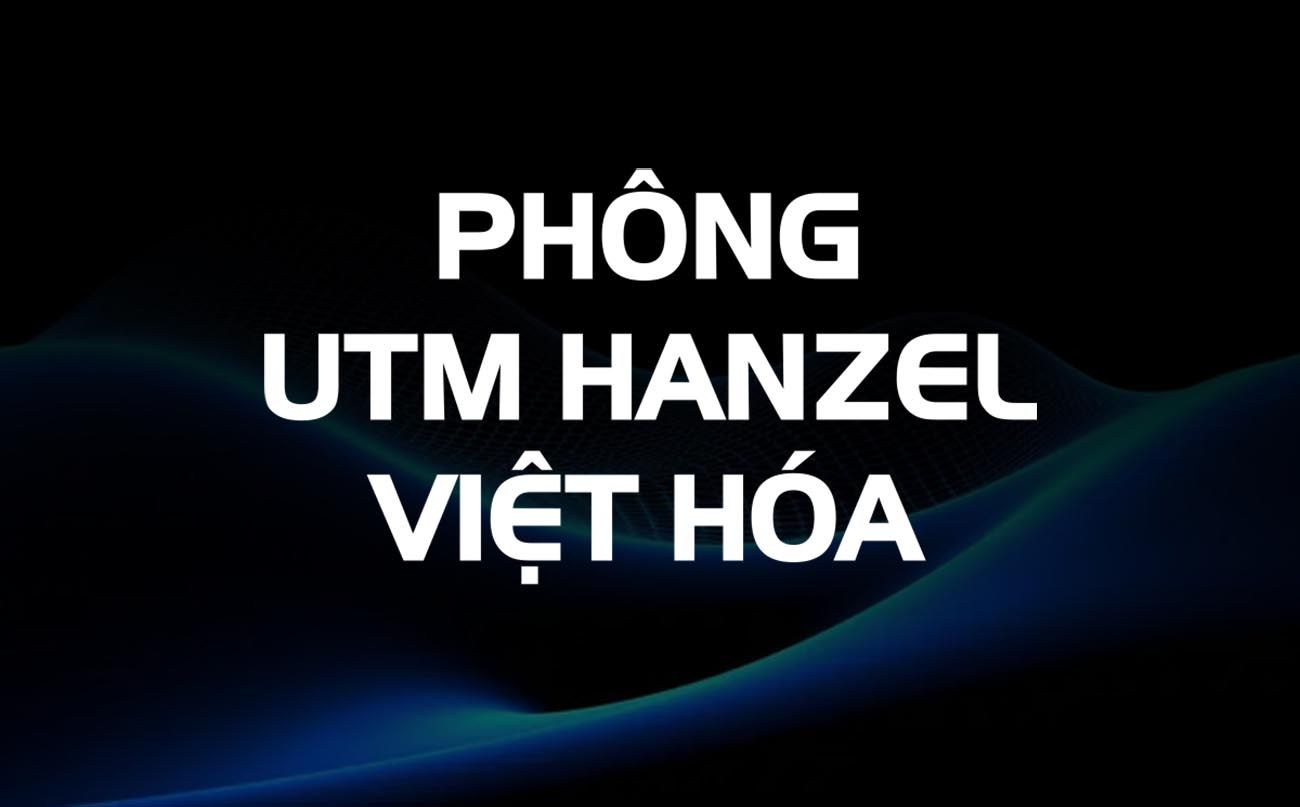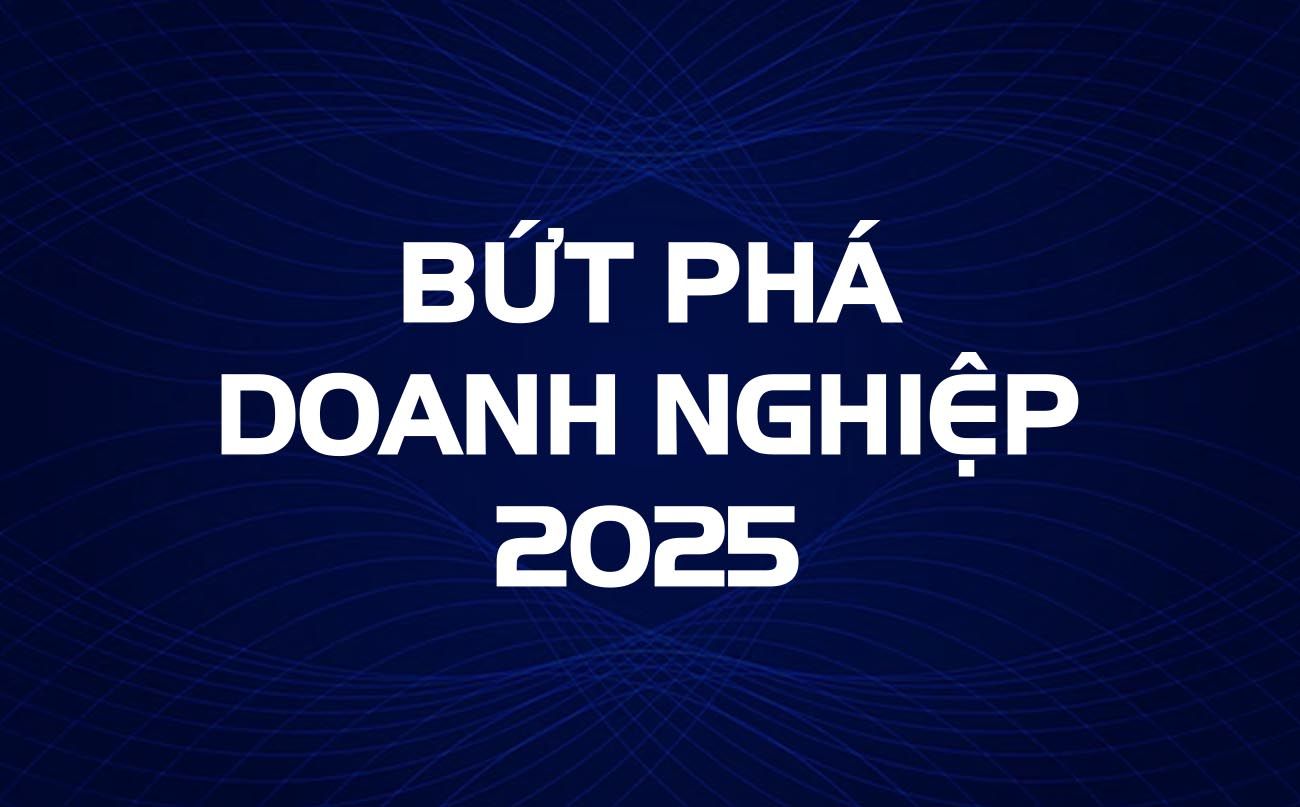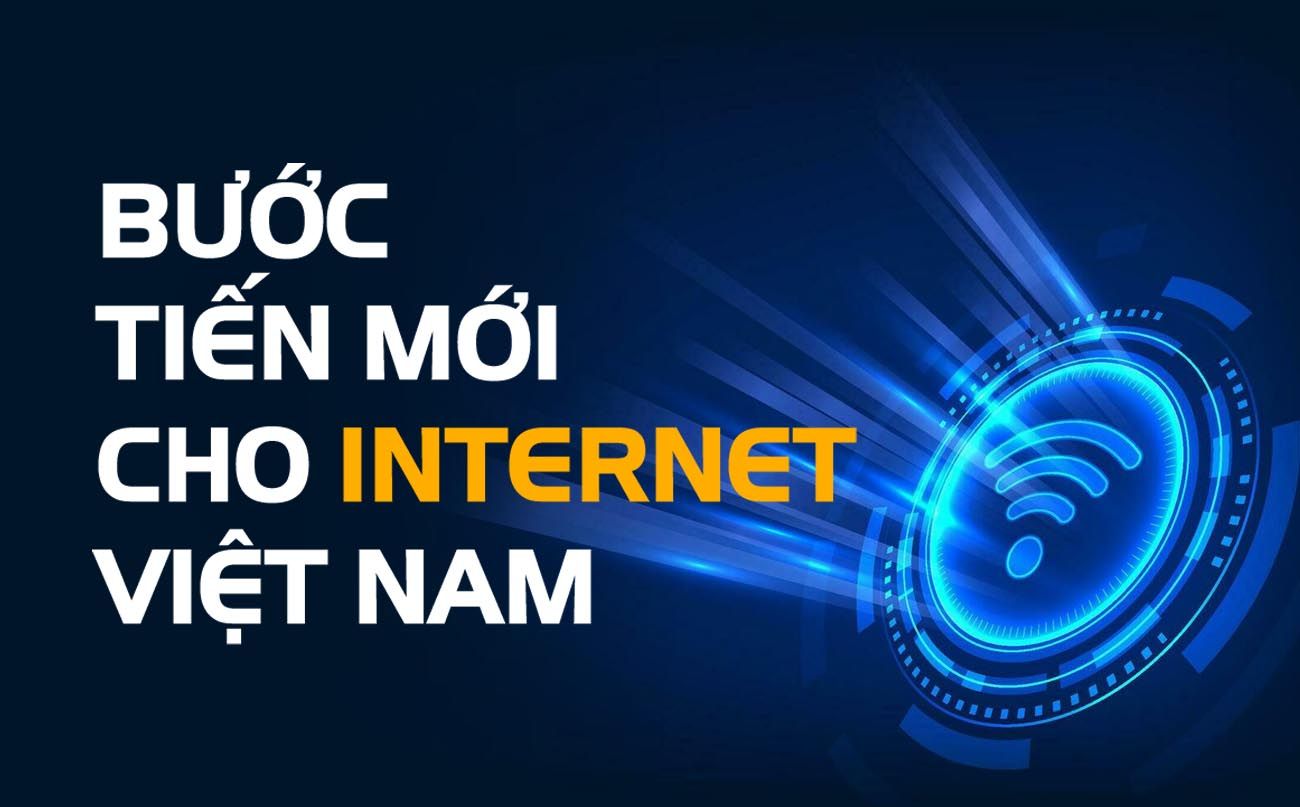
![[Tải Xuống] Font UTM Hanzel – Phông Chữ Không Chân Mạnh Mẽ, Hiện Đại & Việt Hóa Đầy Đủ](https://cdn.s99.vn/z0/833b639681e4a01026c63ca058c85869/p/vvvbg8h43o/68ce32b742df687a95bf47350e797ad2.jpeg)
Bạn đã từng cảm thấy khó chịu vì một font chữ quá rối rắm, thiếu điểm nhấn hoặc không hỗ trợ tiếng Việt? Nếu đang tìm kiếm một kiểu chữ vừa gọn gàng, vừa mạnh mẽ, lại dễ dùng cho mọi dự án thiết kế – thì font UTM Hanzel có thể chính là điều bạn đang cần. Đây là bản Việt hóa hoàn chỉnh của font Hanzel – một phông chữ sans-serif đậm chất hình học, mang lại cảm giác hiện đại, thể thao và đầy sức sống.
UTM Hanzel là phông chữ không chân được Việt hóa bởi nhóm Urban Type Management – những người đã giúp hàng trăm nhà thiết kế Việt Nam tiếp cận font đẹp chuẩn quốc tế. Với các đường nét sắc sảo, mạnh mẽ nhưng vẫn tối giản, font này không chỉ dễ đọc mà còn truyền tải sự quyết đoán, linh hoạt – rất phù hợp cho thiết kế tiêu đề, logo hoặc các chiến dịch truyền thông năng động. Bạn đang làm poster cho một giải đấu thể thao, hay cần tạo điểm nhấn cho thương hiệu cá tính? UTM Hanzel sẵn sàng đồng hành.
Trước tiên là cảm giác chắc chắn. Mỗi con chữ trong UTM Hanzel đều có tỉ lệ hình học chặt chẽ, nét cắt dứt khoát và bo góc khéo léo – vừa mạnh mẽ, vừa thân thiện. Sự đơn giản chính là điểm cộng lớn nhất: không màu mè, không phá cách quá đà, chỉ tập trung vào việc truyền tải thông điệp một cách rõ ràng nhất.
Điều tuyệt vời là font hỗ trợ đầy đủ tiếng Việt, từ dấu sắc, huyền đến chữ hoa, chữ thường – giúp bạn an tâm sáng tạo trong mọi dự án nội địa. Đặc biệt, nếu bạn đang thiết kế sản phẩm thiên về thể thao, giáo dục hoặc các lĩnh vực đòi hỏi sự chuyên nghiệp, thì font này là một lựa chọn không nên bỏ qua.
Bạn là designer đang chạy deadline banner cho một sự kiện thể thao? Hay marketer cần trình bày một slide chỉn chu nhưng không khô khan? Hoặc đơn giản là bạn cần một font chữ “nhìn một lần là nhớ”? Dù là trường hợp nào, UTM Hanzel đều có thể đáp ứng.
Font cực kỳ hiệu quả khi dùng trong các thiết kế như: poster thể thao, typography cổ động, tiêu đề thương hiệu startup, social media banner, slide thuyết trình hay thậm chí là logo. Kiểu dáng không chân hiện đại giúp bạn dễ phối hợp với các font khác mà vẫn đảm bảo độ nhận diện cao.
Trong một rừng font chữ, không dễ để tìm được một kiểu vừa đơn giản, vừa có cá tính rõ ràng. Nhưng UTM Hanzel làm được điều đó. Nó mang vẻ đẹp hình học hiện đại, nét mạnh mẽ không phô trương, cùng khả năng ứng dụng rộng rãi từ thể thao đến truyền thông chuyên nghiệp. Nếu bạn muốn thiết kế của mình trở nên rõ ràng, nổi bật và đáng nhớ – đừng bỏ qua font chữ này.